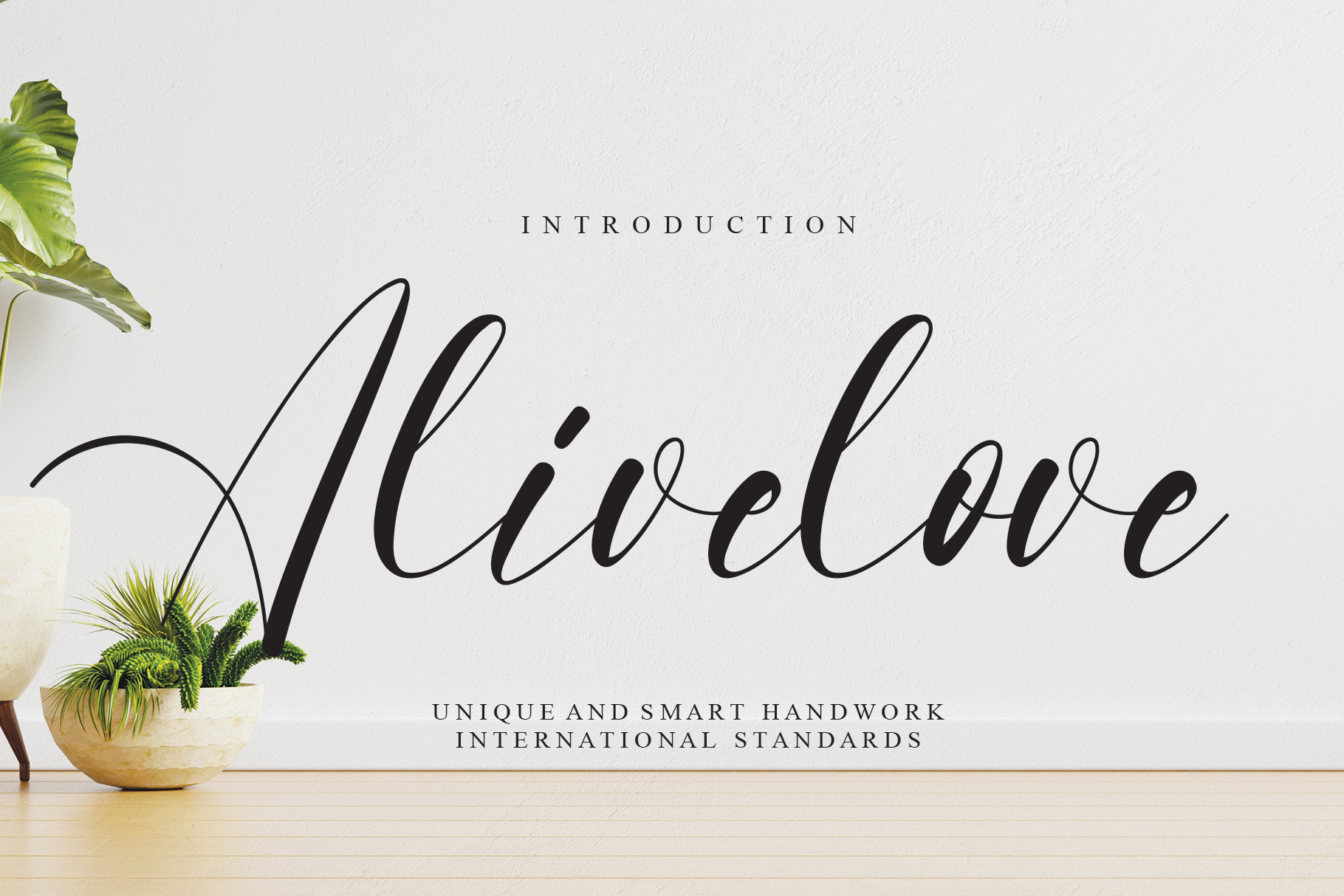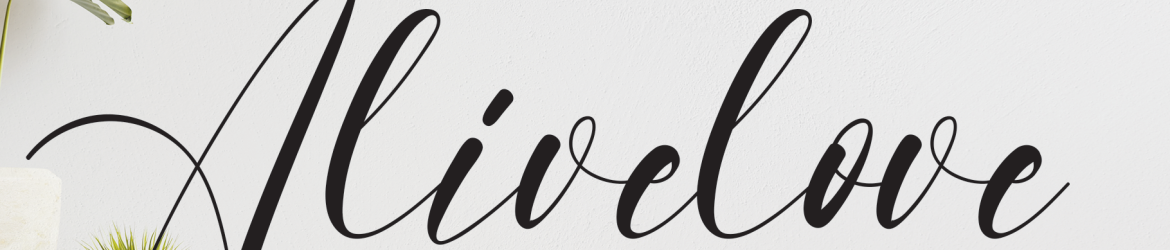
A “Alivelove Font” é uma elegante tipografia feita à mão que adiciona um toque único a qualquer projeto visual. Inspirada no estilo delicado e íntimo do texto escritos de forma livre, esta fonte leva o design para um patamar mais luxuoso e sofisticado. Suas linhas suaves e nuances sutis criam um impacto poderoso, tornando-a uma escolha ideal para adicionar elegância a qualquer projeto que você tenha em mente. Combinada com os recursos gráficos do creativeletter, esta font oferece uma maneira singular de dar vida às ideias e transformá-las em algo realmente especial.